История кириллицы: от глаголицы до современного алфавита
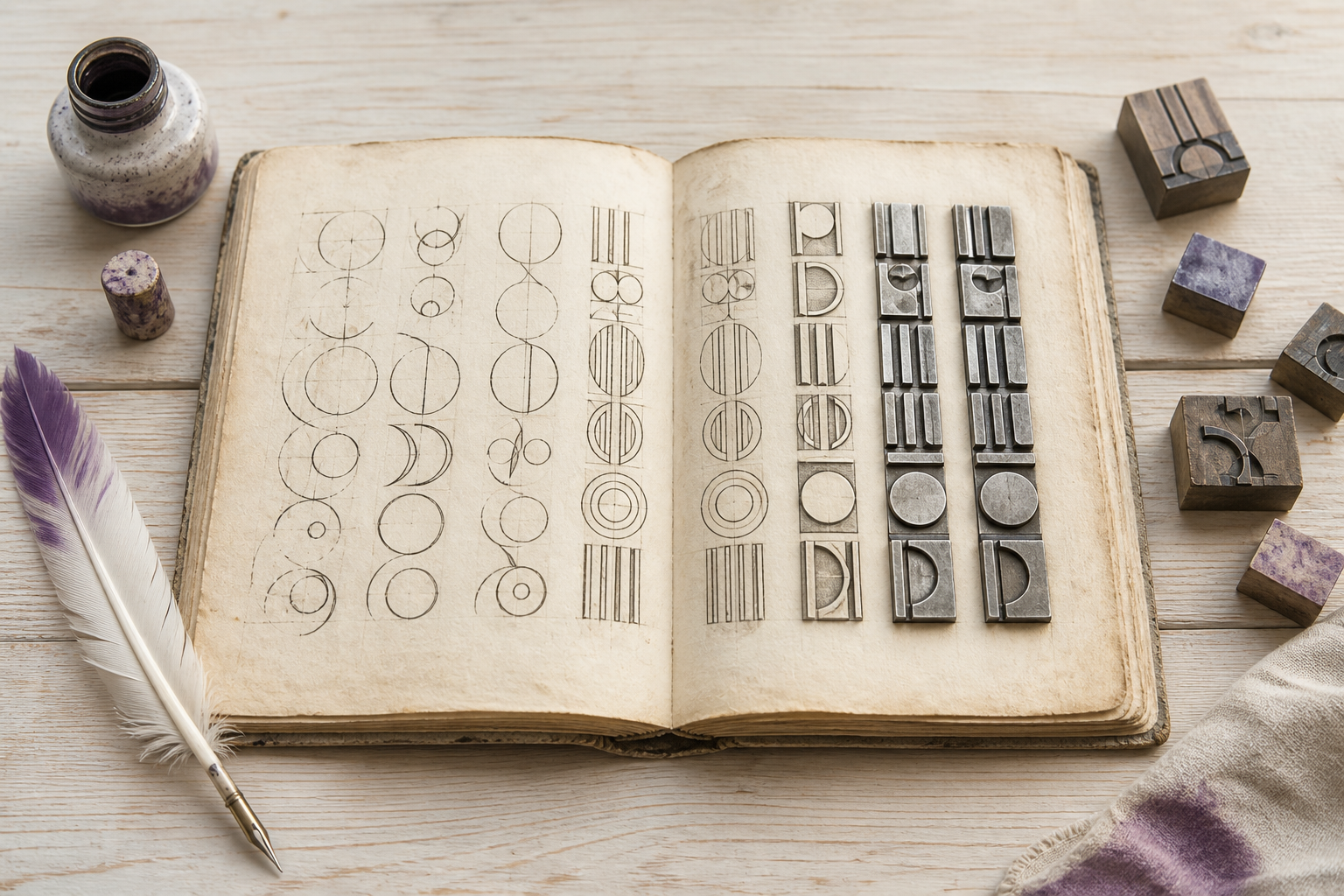
История кириллицы — это последовательное развитие славянской письменности от глаголицы и ранних книжных рукописей к кириллическому алфавиту, уставу, полууставу и современным печатным формам. В статье разберём, как менялись знаки, какие реформы повлияли на русский язык и что важно учитывать при создании кириллического шрифта.
Что такое кириллица и откуда она появилась
Кириллица — это система письма, которая используется для записи русского, болгарского, сербского, украинского, белорусского, македонского и ряда других языков. Её возникновение связано с христианской миссией среди славян в IX веке, деятельностью Константина-Кирилла и Мефодия, а также работой их учеников в славянских книжных центрах.
Название «кириллица» традиционно связывают с именем Кирилла, однако вопрос о непосредственном авторстве алфавита требует осторожности. Историки обычно различают две системы: глаголицу, более раннюю славянскую азбуку, и кириллицу, сформировавшуюся позднее на основе греческого письма с добавлением знаков для славянских звуков.
Глаголица: первая славянская книжная азбука
Глаголица считается первой специально созданной славянской системой письма. Её связывают с Константином-Кириллом и переводческой деятельностью IX века. Знаки глаголицы заметно отличаются от греческих и латинских букв: многие из них построены на сочетании кругов, крестов, дуг и сложных геометрических элементов.
Главная задача глаголицы заключалась не в декоративности, а в точной передаче звуков славянской речи. Для этого в ней появились отдельные знаки, которых не хватало в греческом алфавите. Глаголические рукописи читались в славянской богослужебной традиции, а сама система письма особенно долго сохранялась в хорватской церковной культуре.
Для современного читателя глаголица может выглядеть непривычно, потому что её буквы не образуют очевидной связи с привычными А, Б, В и Г. При этом историческая ценность глаголицы огромна: она показывает, что славянская письменность изначально создавалась как самостоятельная графическая система, а не просто как механическая адаптация чужого алфавита.
Как сформировалась кириллица
Кириллица сложилась в конце IX — начале X века в среде учеников Кирилла и Мефодия, прежде всего в Болгарском царстве. За основу графики был взят греческий книжный маюскульный алфавит, близкий к византийскому унциалу. Для звуков, которых не было в греческом языке, использовали специальные славянские буквы, часть которых восходила к глаголической традиции.
Такое происхождение объясняет двойственный характер кириллицы. Одни буквы легко узнаются как греческие аналоги: А, В, Е, К, М, Н, О, Т и другие. Другие знаки были необходимы для славянской фонетики: Ж, Ц, Ч, Ш, Щ, Ы, Ю, Я. В результате появилась система, одновременно связанная с византийской книжной культурой и приспособленная к славянским языкам.
Устав: строгая форма ранней книжной письменности
Устав — это ранний тип кириллического книжного письма, особенно характерный для богослужебных рукописей. Его отличают крупные отдельные буквы, чёткий ритм строки, отсутствие привычного строчного начертания и тщательно выверенные пропорции. Текст устава строился как последовательность самостоятельных знаков, поэтому письмо выглядело монументально и хорошо сохраняло структуру страницы.
В рукописном уставе большое значение имели материал и инструмент. Переписчик работал пером на пергамене или бумаге, регулировал толщину штриха нажимом и углом пера, а заглавные буквы и отдельные фрагменты мог выделять красной краской. Отсюда происходит термин «красная строка» — первоначально она была связана с цветовым выделением начала текста.
Устав нельзя полностью отождествлять с современным шрифтом. Это прежде всего способ письма и система организации рукописного текста. Однако для дизайнера устав остаётся важным источником визуальных решений: его можно изучать по характеру засечек, ширине букв, контрасту штрихов, пропорциям знаков и расстояниям между словами.
Полуустав и скоропись: от книжной строгости к скорости
Полуустав появился как более свободная и компактная форма письма. По сравнению с уставом его буквы обычно меньше, движения пера становятся разнообразнее, а строки могут быть плотнее. Полуустав был удобен для рукописей, которые требовали экономии материала и более быстрого переписывания, поэтому постепенно вытеснял строгий устав в части книжной практики.
Скоропись развивалась прежде всего как практическое письмо для документов, заметок и деловой переписки. В ней буквы соединялись, сокращались и меняли форму в зависимости от соседних знаков. Читаемость сохранялась благодаря общему контексту, но отдельная буква в скорописи могла сильно отличаться от её уставного образца.
Эти три формы полезно рассматривать как разные режимы работы с текстом. Устав подчёркивает торжественность и устойчивость, полуустав сочетает книжность с компактностью, а скоропись передаёт скорость и личный жест. В современной типографике такое различие помогает точнее выбирать стилистический источник для логотипа, афиши, упаковки или исторической реконструкции.
Краткий вывод
История кириллицы начинается с формирования славянской книжной письменности, проходит через глаголицу, кириллицу, устав, полуустав и гражданский шрифт, а затем приводит к современным цифровым гарнитурам. Понимание этих этапов помогает точнее читать исторические источники и осознанно использовать кириллическую графику в дизайне.